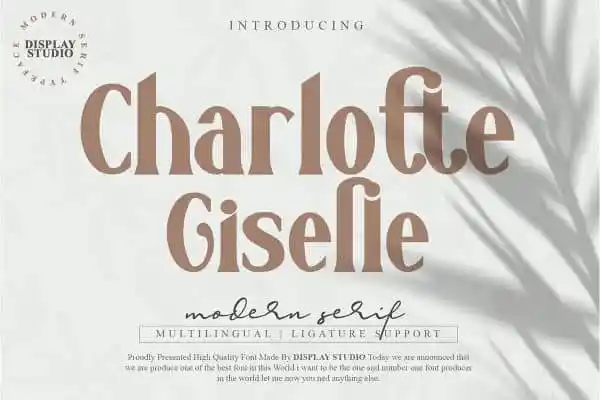
Charlotte Giselle Serif Font – Download Grátis
A Charlotte Giselle Serif Font é apresentada aqui para os designers que buscam trazer elegância clássica à suas criações digitais. Este tipo de letra serif moderna e nostálgica oferece uma mistura perfeita de classe e atualidade, ideal tanto para logotipos quanto para ambientes impressos como revistas ou redes sociais. Essa fonte está pronta para uso imediato em suas próximas criações design, já que foi projetada para complementar e se destacar juntos com outras serifas. Se você procura uma maneira de incluir nuances de elegância, estilo sofisticado e modernidade em seus designs, a Charlotte Giselle Serifa é o elemento perfeito para sua coleção de fontes.